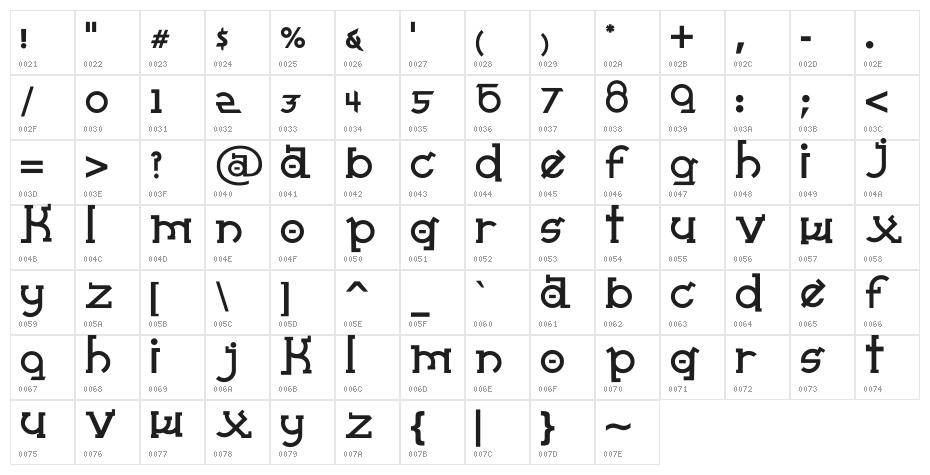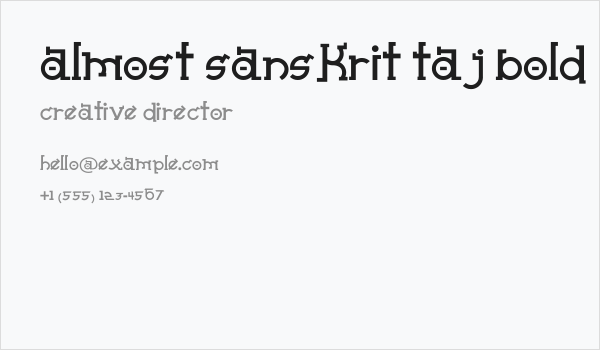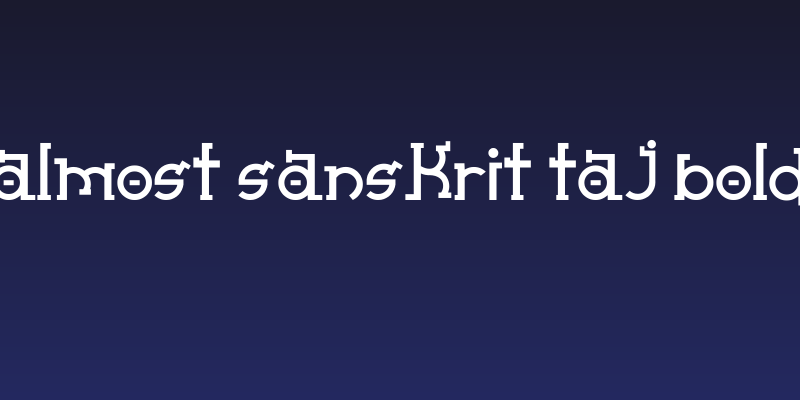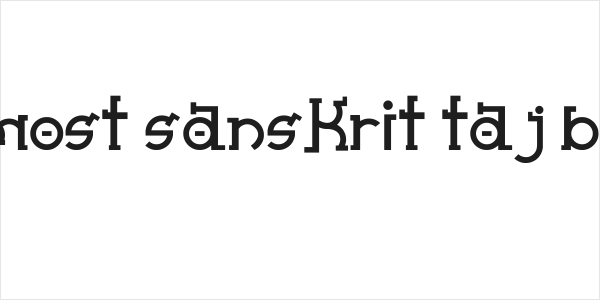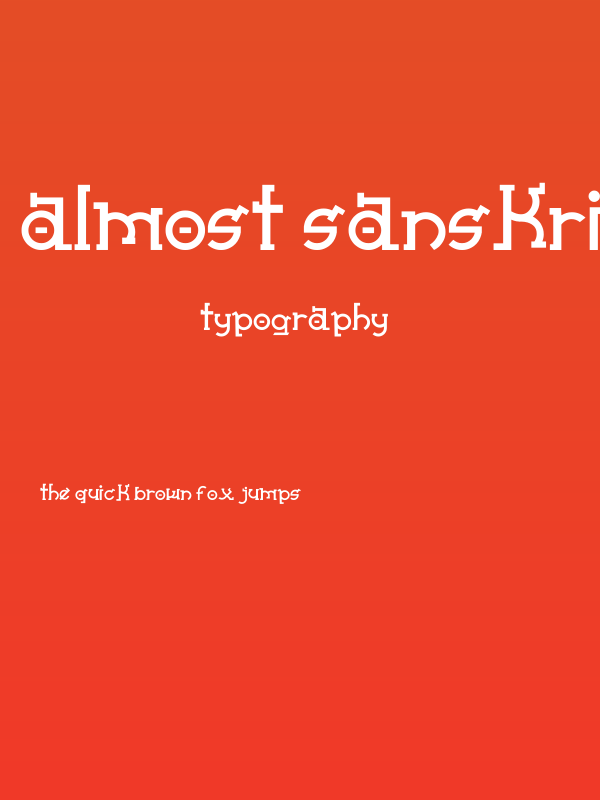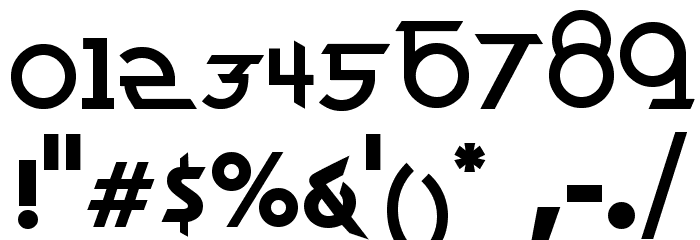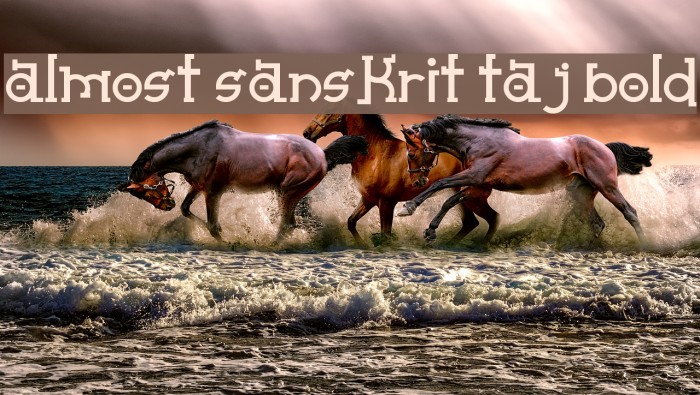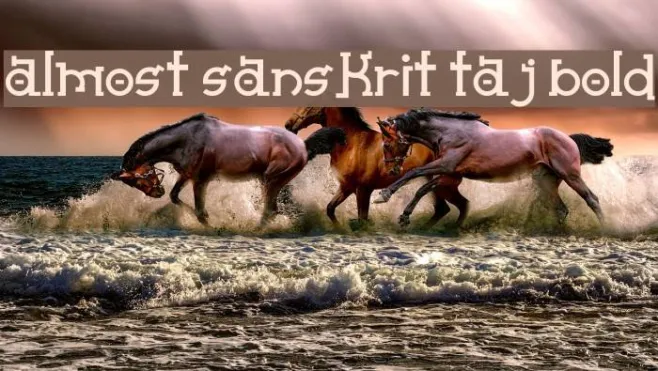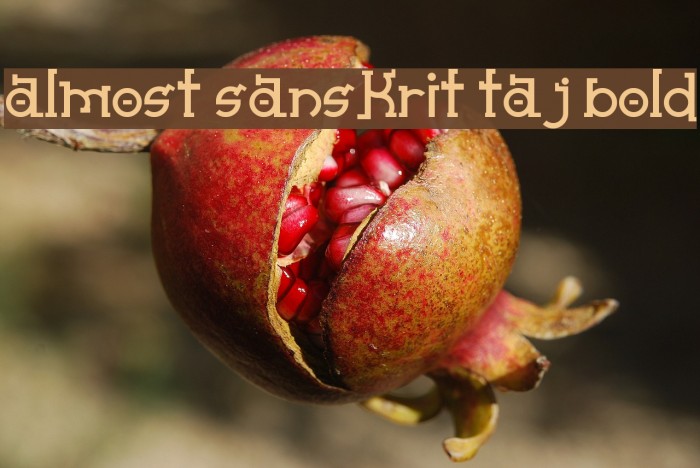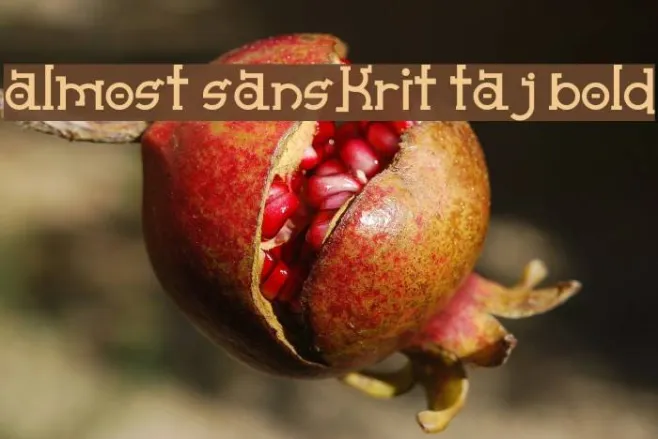
Almost Sanskrit taj Bold Font
| Projets proposés | Ideal for projects that require a cultural or historical touch, such as event posters, book covers, or branding for cultural events. |